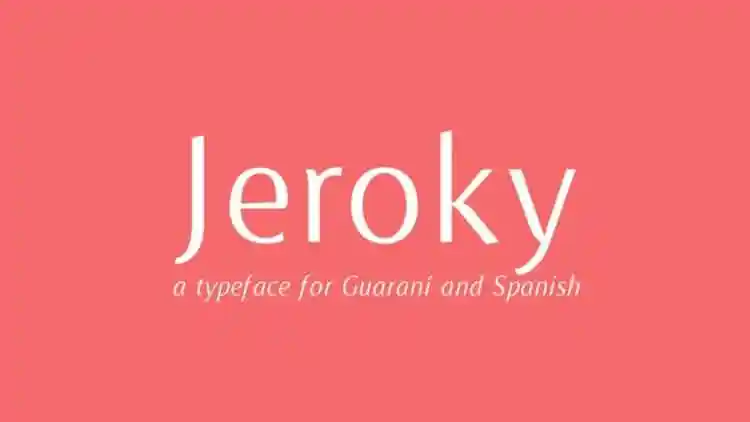
Jeroky Sans Serif Font
A Jeroky Sans Serif é uma tipografia sans-serif que Juan Heilborn criou para introduzir alegria e aconchego em designs minimalistas. Com seu ar humanista, esta fonte faz mais do que apenas complementar um design limpo: ela oferece um toque de vida ao texto. Ideal para textos educacionais e informativos, a Jeroky é rápida e fácil de ler graças à sua suporte ao guarani e espanhol. Esta tipografia é perfeita para quem busca uma fonte moderna que se encaixa em ambientes informais e educativos sem perder o toque amigável e sofisticado do seu design. Seja você um criador de conteúdo, designer ou qualquer outro profissional que precisa de uma fonte atenta aos detalhes, a Jeroky Sans Serif é o elemento ideal para tornar seus projetos ainda mais únicos e envolventes.